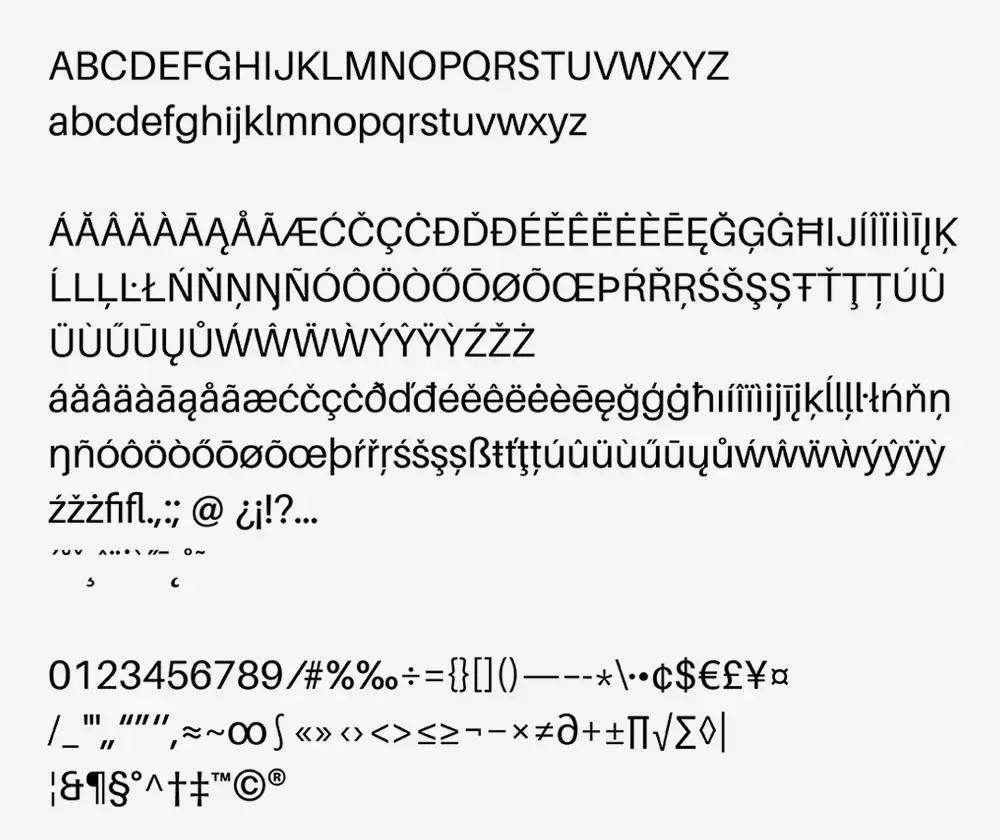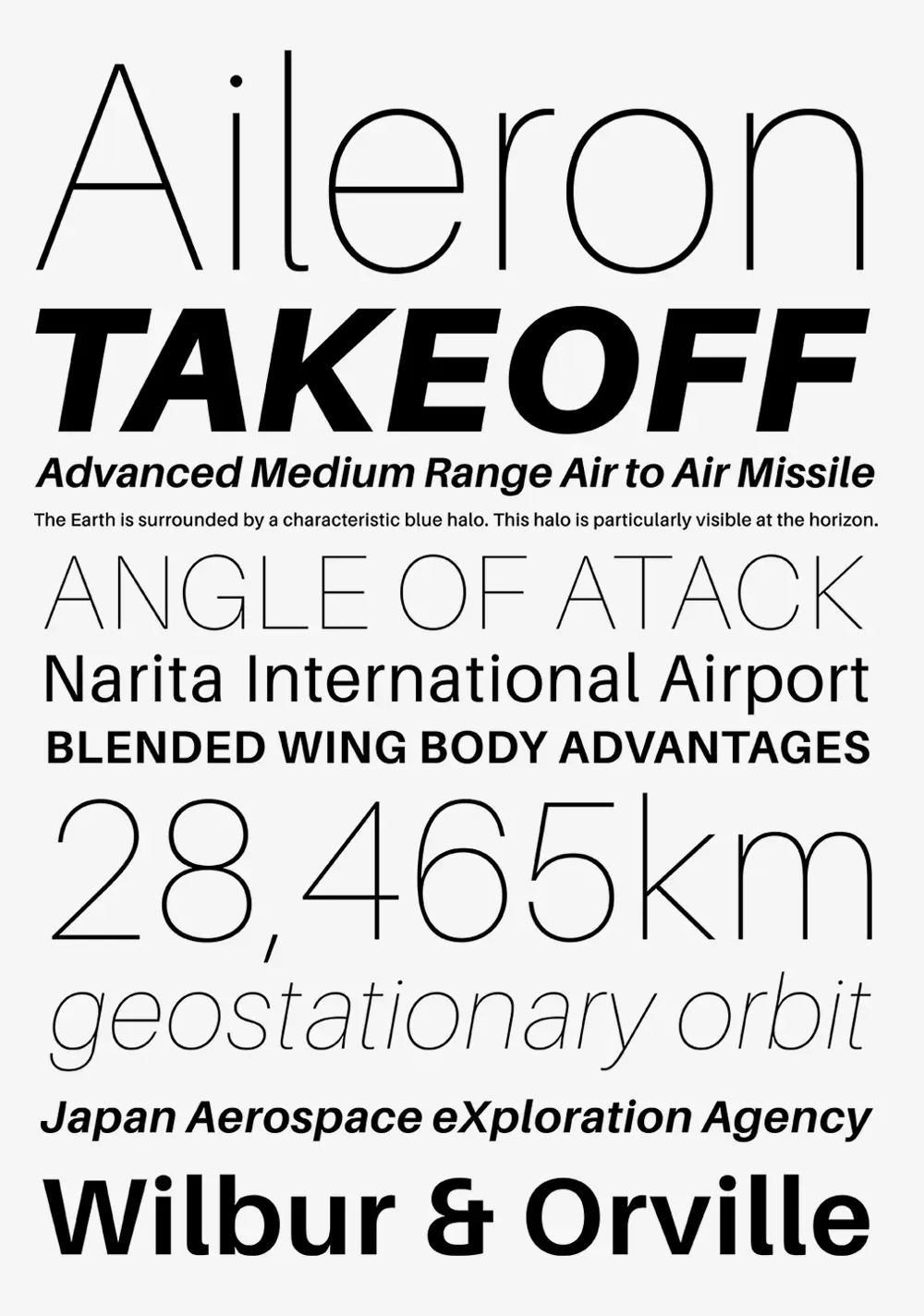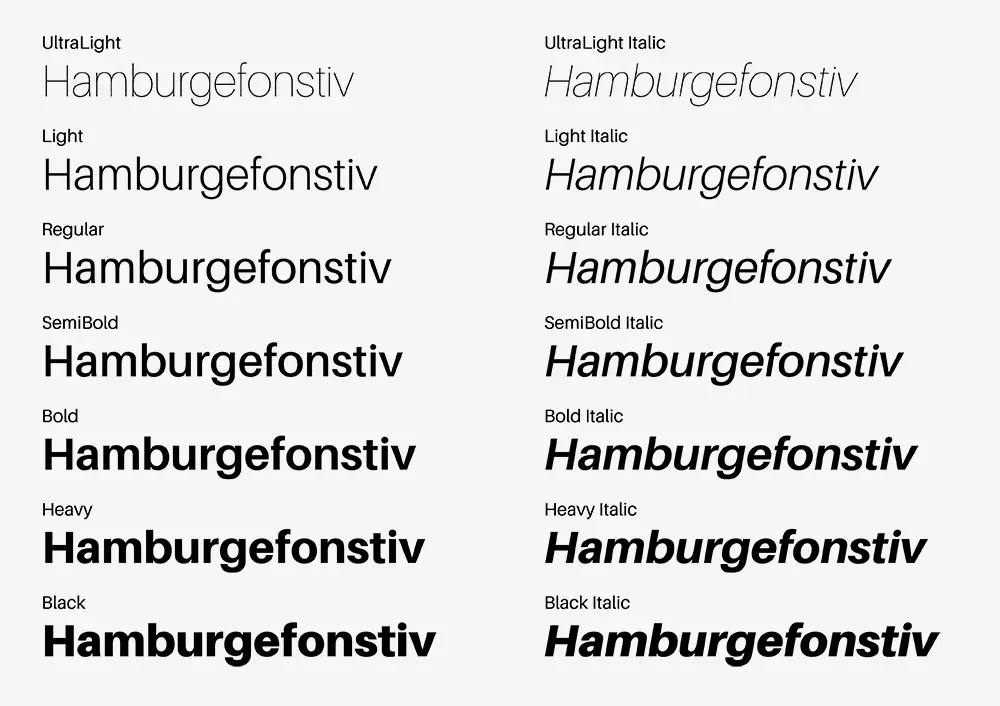
Aileron 是一種無襯線字體,基於 Helvetica 等新怪誕字體,並添加了我自己的解釋。
作為對文字的調整,字母之間的間距稍微變寬,小寫字母“L”的末端已彎曲,以便更容易將其與大寫字母“I”區分開。
另外,“i”、“j”、句號等圓點都被做成了圓形,彎曲的部分也被處理成類似迴旋曲線的形狀,整體給人一種柔和的感覺。在設計上,它與 Helvetica 類似,但在概念上,它與 Univers 更相似。
此外,這是我們第一次準備斜體版本的點冒號字體。基本上,它是機械傾斜的,但已經進行了視覺修正,因此不會感到奇怪。
利用多重主控的優勢,提供從超輕到黑色的 8 個重量級別。我認為它可以用於多種情況。
2021 年 12 月,我們發佈了Nacelle作為更新版本。
Aileronは、Helveticaをはじめとするネオグロテスクに分類される書體を參考に、自分なりの解釈を追加しまとめたサンセリフフォントです。
本文向けの調整として若干字間を広めにし、大文字アイ「I」との識別をしやすくするため、小文字エル「l」の末端部分をカーブさせたデザインにしています。
ほか、「i」や「j」やピリオドなどのドット部分を円形に、曲線部分にクロソイド曲線を意識した処理を施す事で、全體的に柔らかい印象が出るようにしました。デザイン的にはHelveticaに近いですが、コンセプト的にはむしろUniversに近いものになっています。
また、今回ドットコロンのフォントとしてはじめてイタリック體を用意しています。基本は機械的に傾けたものですが、違和感のないように視覚補正を施しました。
マルチプルマスターを生かし、ウェイトはUltraLightからBlackまで8段階を用意。広い場面で使っていただけると思っています。
2021年12月に、バージョンアップ版としてNacelleを公開しました。